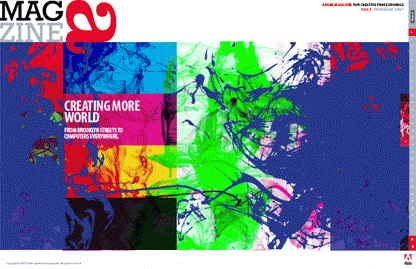
Adobe a édité un magazine au format pdf. Ce serait une nouvelle banale si l’on se réfère à l’ensemble des magazines disponibles en ligne dans ce portable document format. Mais il y a deux aspects (au moins) qui valent la peine de se pencher sur la question.
1) aspect graphique et
2) le modèle économique
Du point de vue strictement éditoriale aucune remarque particulière. L’opérateur historique de la typo et de l’image voit large. Le magazine balaye un champ de possibles visuels qui correspond à chacun des segments de son marché très étendu. Mais en *feuilletant* rapidement le pdf, on se rend bien compte qu’il y a un problème de cohérence éditoriale et graphique. On ne peut pas plaire à tout le monde: étudiants, graphistes seniors, photographes, webdesigners et services de marketing, autant dire c’est le grand écart visuel d’une page à l’autre, d’une rubrique au suivant. Non qu’il y ait foncièrement faute de goût pour chacune des cibles concernées.
Nous pourrions bien entendu critiquer tel ou tel détail. Des pavés de textes très souvent indigestes aux justifs trop longues. Mais au fond l’essentiel n’est pas là. Il demeure dans la disparité du Mag, dans le manque de cohérence dans la narration d’Adobe vis à vis de son très vaste public. Émetteur de message Adobe, oui mais avant tout créateur de logiciels qui ont révolutionné la planète entière. Cela ne les prive pas de l’obligation de réflexion sur l’art et la manière de toucher leurs lecteur. Il me semblerait plus judicieux par exemple de s’adresser de façon homogène à chacun de ses segments de marché identifié. Photographes et graphistes ne cherchent pas les mêmes solutions et ne vivent pas leur écran quotidien de la même façon.
Webdesigners et graphistes print ne cherchent pas les mêmes logiciels et la même articulation entre-eux. Les responsables marketing, bien que sans doute portés à s’intéresser à la création graphique ne ressentent pas le même intérêt pour la typographie que les graphistes créateurs d’alphabets et d’identités visuelles. Le mot qui me vient à l’espri: c’est une communication qui postillonne. Tout le monde en reçoit pour son grade. Et cela n’empêche pas qu’on reste aficionados de leurs produits. Il s’agit tout bonnement de responsabilité dans l’analyse d’une stratégie de comm. On aurait pu imaginer autant de micro magazine différents qu’il y a de récepteurs-public à toucher. D’élaborer une ligne éditoriale commune et en même temps spécifique à chacune des niches à atteindre, ce qui eut permis de créer une ligne graphique de communication par cible. Ce n’est pas les outils qui manquent pour identifier celle-ci. C’est la volonté de faire plus sûrement du business intelligent.
Le modèle économique de la presse magazine print ne souffre pas trop aujourd’hui de ce marché émergeant de la presse en ligne ou en numérique-pdf. Les ventes du print progressent, leurs revenus publicitaires de même. À terme,on peut imaginer des évolutions. Les salles d’attente aux innombrables Marie-Claire, Elle, Match ou Gala von peut-être s’équiper d’écrans qui de plus est rapporteront des ressources financières pour le cabinet dentaire ou de kinésithérapie. Cependant il y a un marché qui sans doute va s’ouvrir beaucoup plus vite au pdf, la presse professionnelle. Celle-ci est sans doute la plus grande consommatrice de papier aujourd’hui comparée à la presse kiosque ou par abonnement grand public.
Et les entreprises ont des besoins de communcation exponentielles. Il n’est pas interdit d’imaginer que dans un avenir proche voire un présent d’aujourd’hui, nombre de PME, TPE voire de grandes entreprises du CAC alimentent leurs stratégies de comm. par des process pdf. Car après-tout il s’agit avant tout de B to B, et la rédaction de cette forme de communication est vorace en espace papier. Alors qu’Adobe ait opté pour le magazine au format pdf, n’étonnera personne. Tout au plus se dira-t-on que cette société phare dans les logiciels de création devrait montrer l’exemple de façon plus probante. Quant au modèle économique il coule de source. La souplesse de la pagination, la diffusion pécuniairement avantageuse sur serveur dédié de dizaine de milliers d’exemplaires sans aucun autre frais que la bande passante générée milite pour cette option.
Il n’en demeure pas moins que si l’on veut faire évoluer ce nouveau type de transmission de message vers une efficacité redoutable, il faut viser haut. Faire de chacun des numéros de véritables collectors que les lecteurs auront envie de stocker sur leurs disques durs. Là seulement on touchera au but visé. Faire adhérer ses clients et prospects à des valeurs partagées segments par segments. Just do It comme disait Sammy Davis Junior, juif, borgne et noir… que d’handicaps qu’Adobe n’a pas à surmonter (humour).